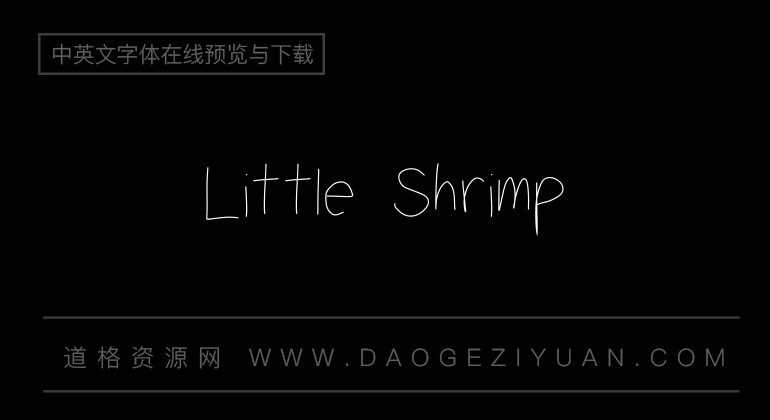
Little Shrimp 是一款由英国设计师Gemma O’Brien设计的手写体字体。它的字体特点是简洁、可爱,充满活力。它的字母具有细节和视觉上的魅力,可以增加文本的吸引力。它是一款完美的字体,可以用于各种类型的文字,如商业广告、海报、书籍封面、标志等。内容介绍
Little Shrimp是一款非常不错的手写艺术字体,具有很好的视觉感,适合于文化类的宣传设计、商业类品牌的广告和产品包装设计以及个性化文字排版等较多场景。